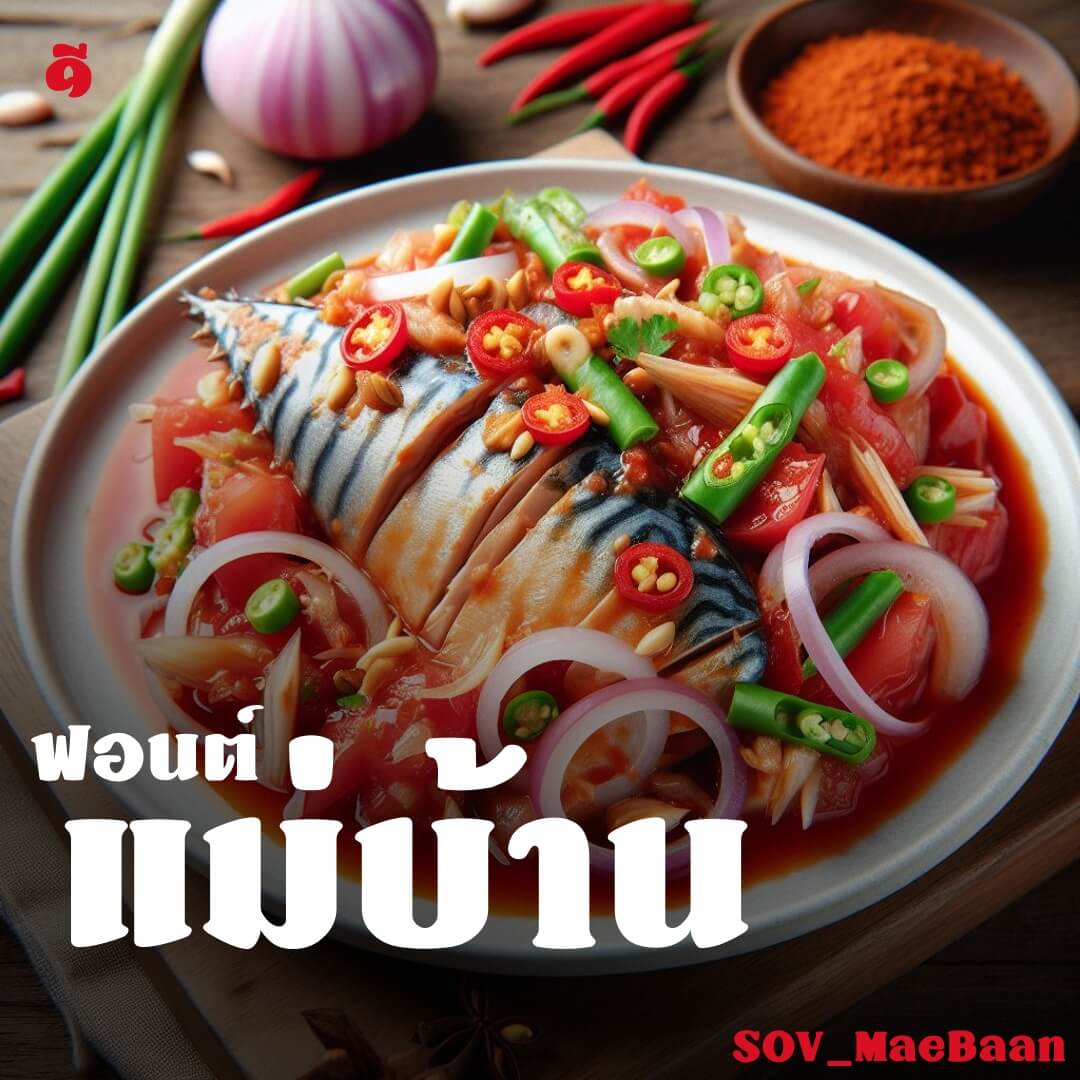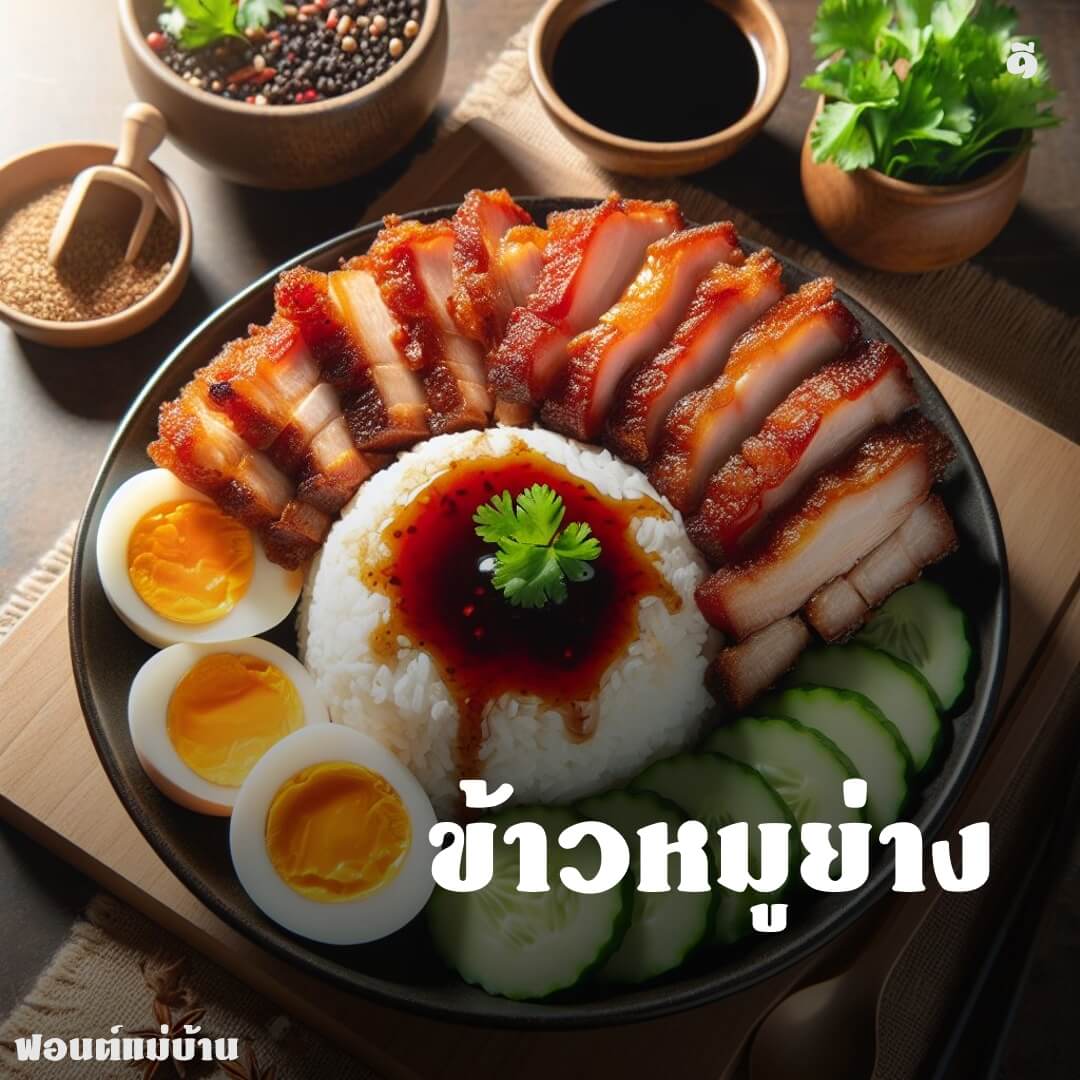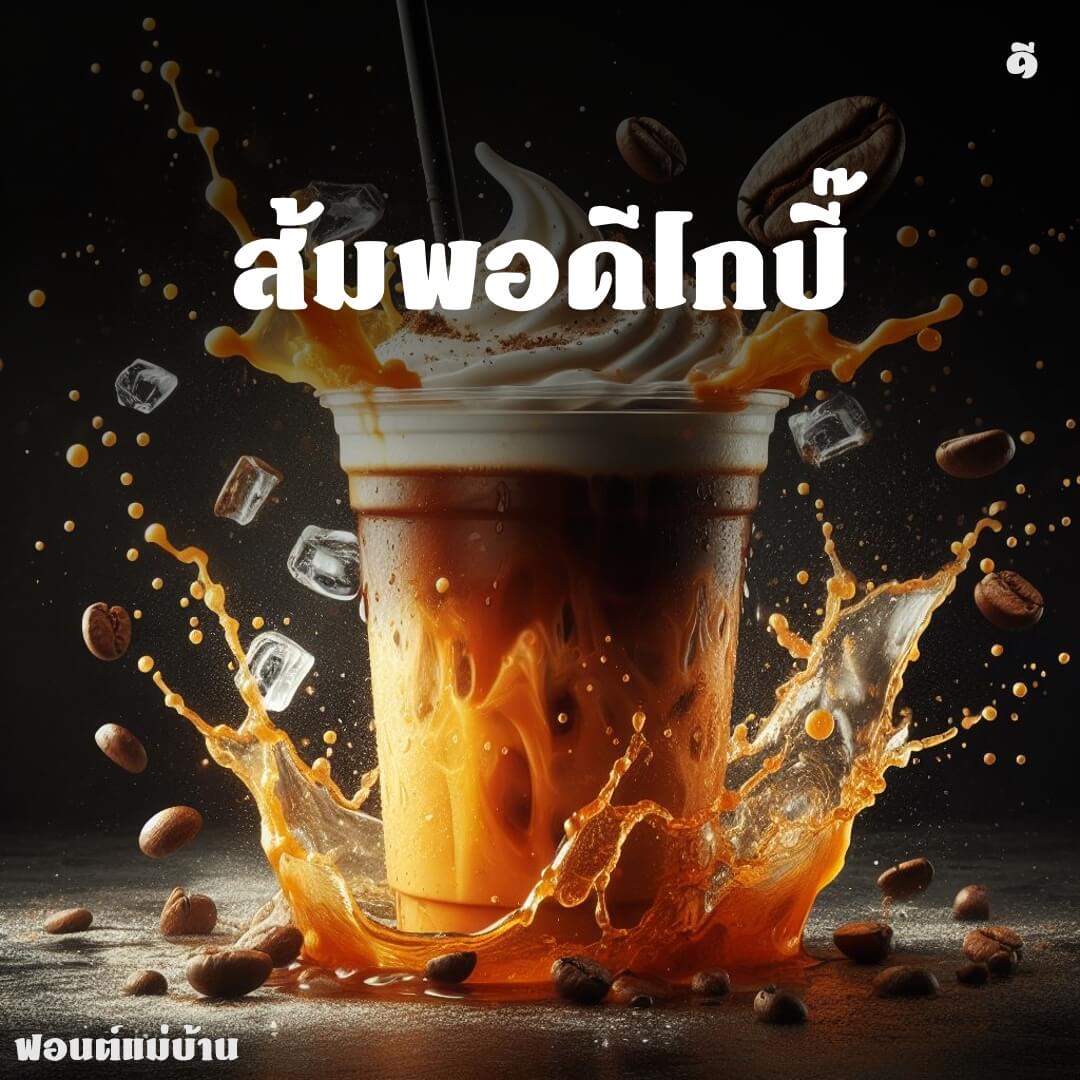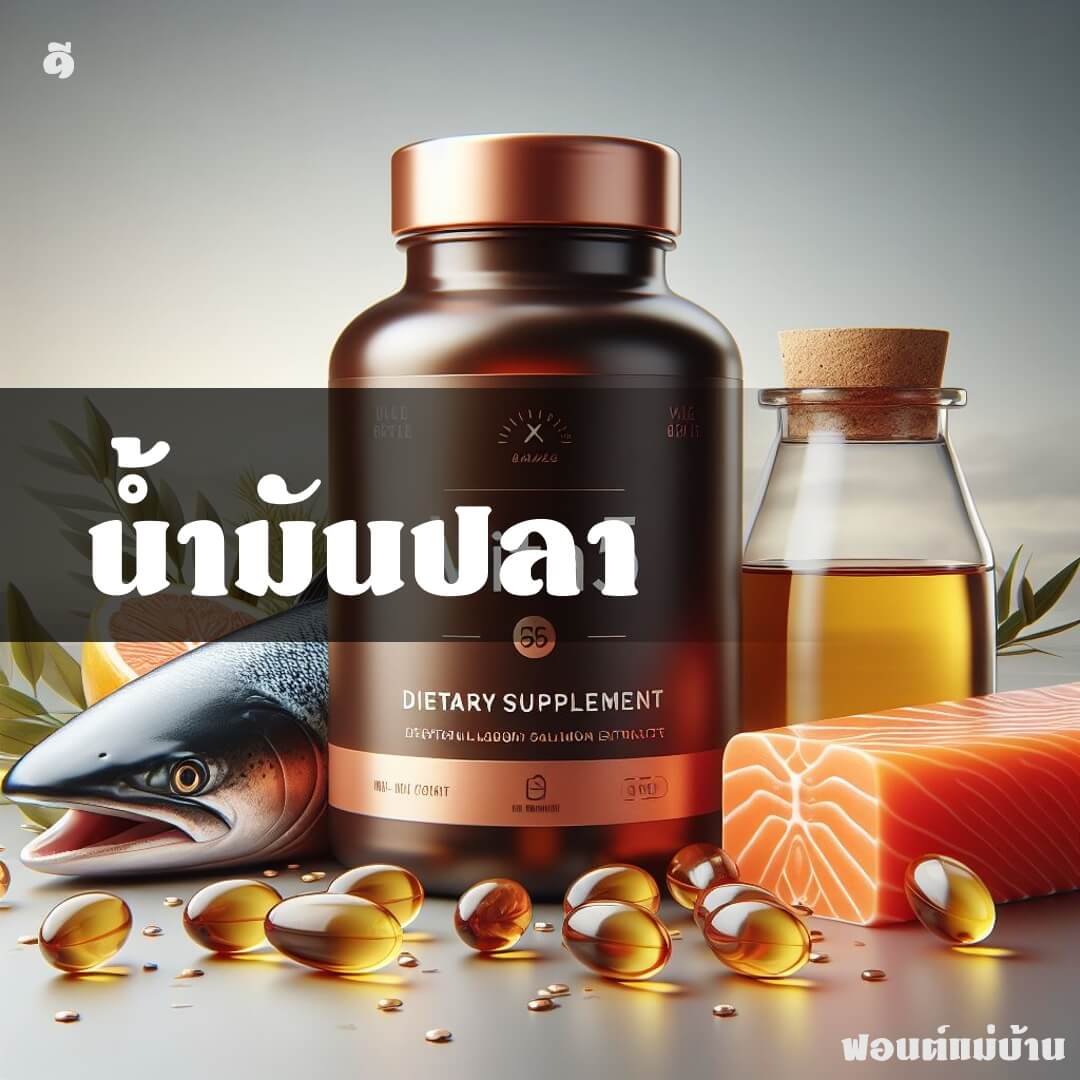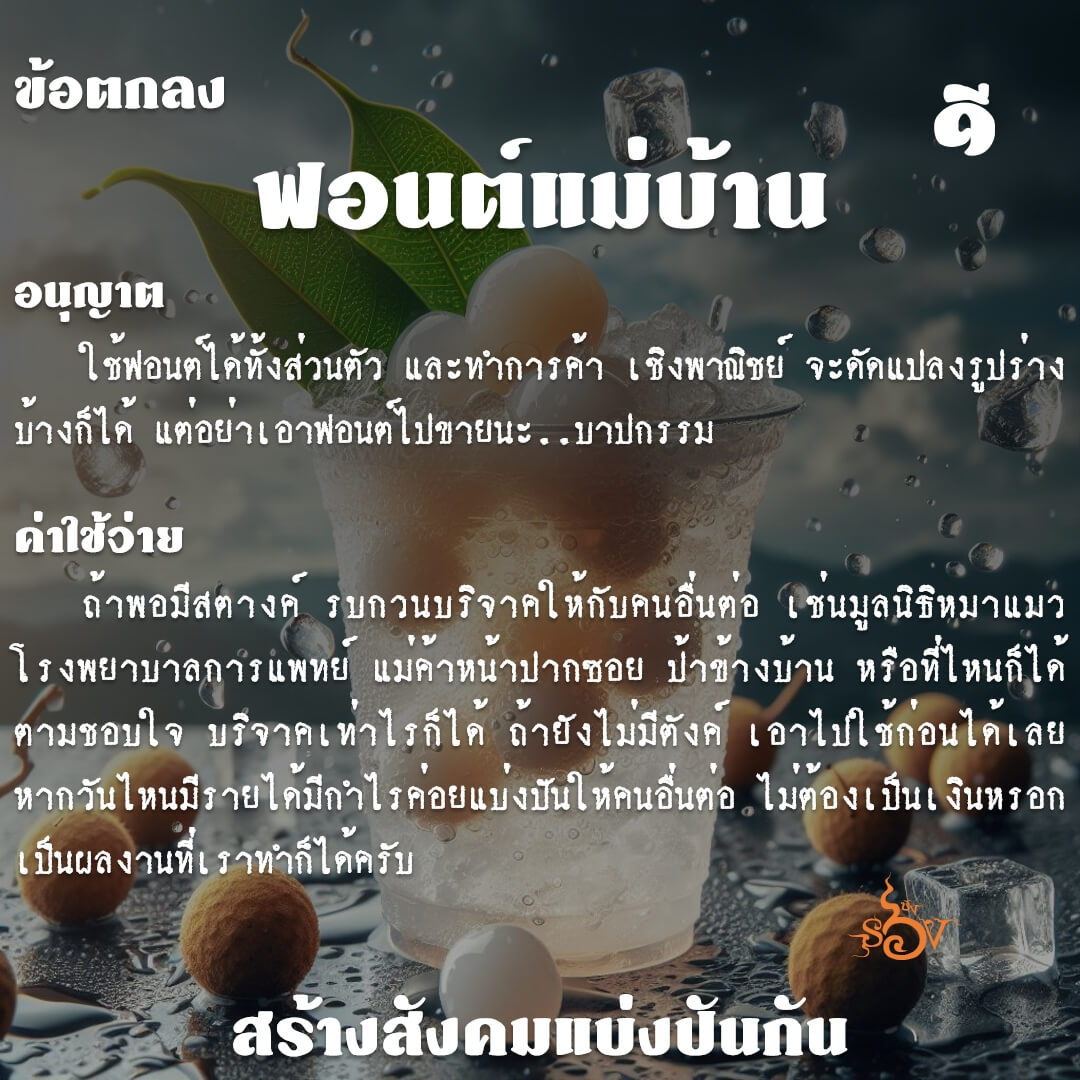
ฟอนต์แม่บ้าน ต้นทางจากหนังสือ “แม่บ้านในฝัน” …ชอบ เพราะให้ความรู้สึกเป็นฟอนต์ Cooper Black อักษรไทย
เบื้องหลังการออกแบบ : ฟอนต์ แม่บ้าน
แม่บ้าน (SOV_MaeBaan)